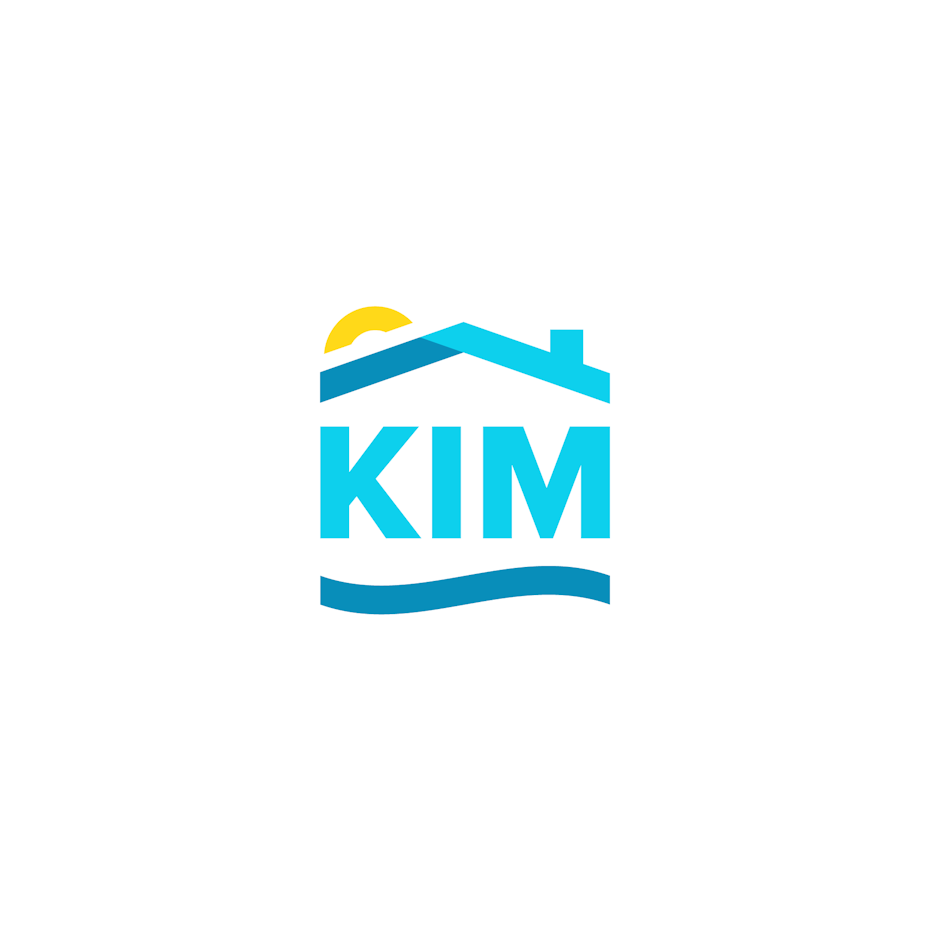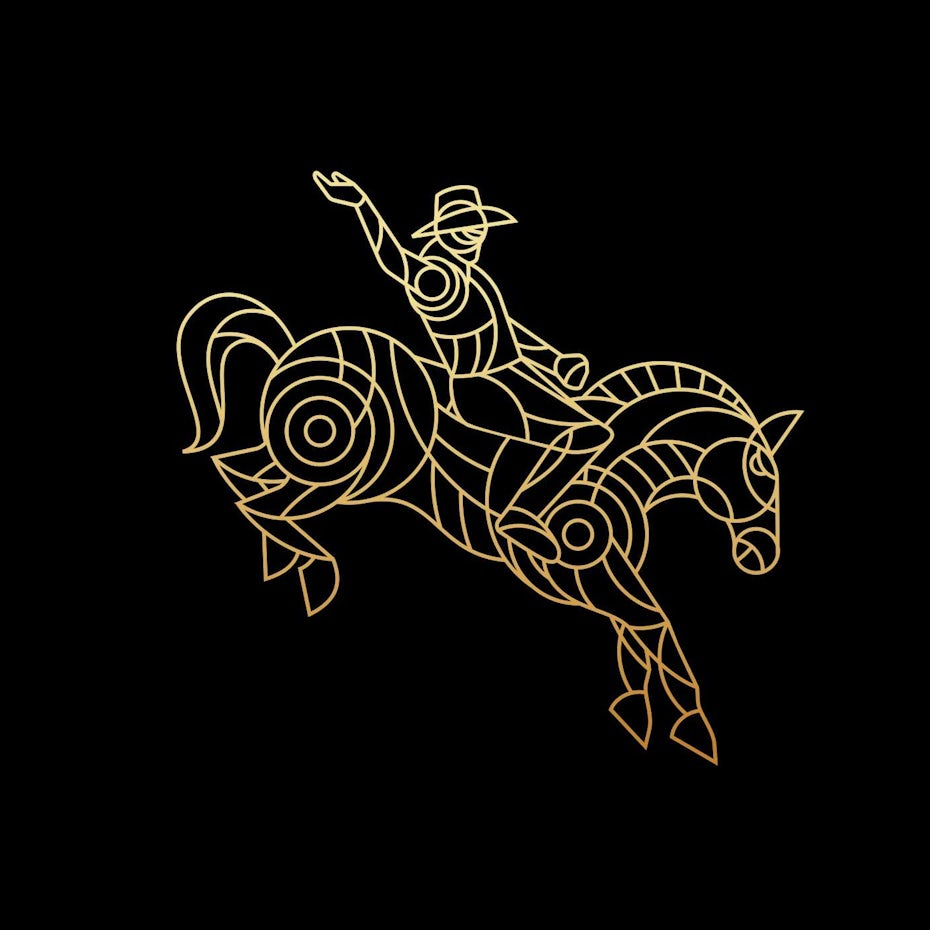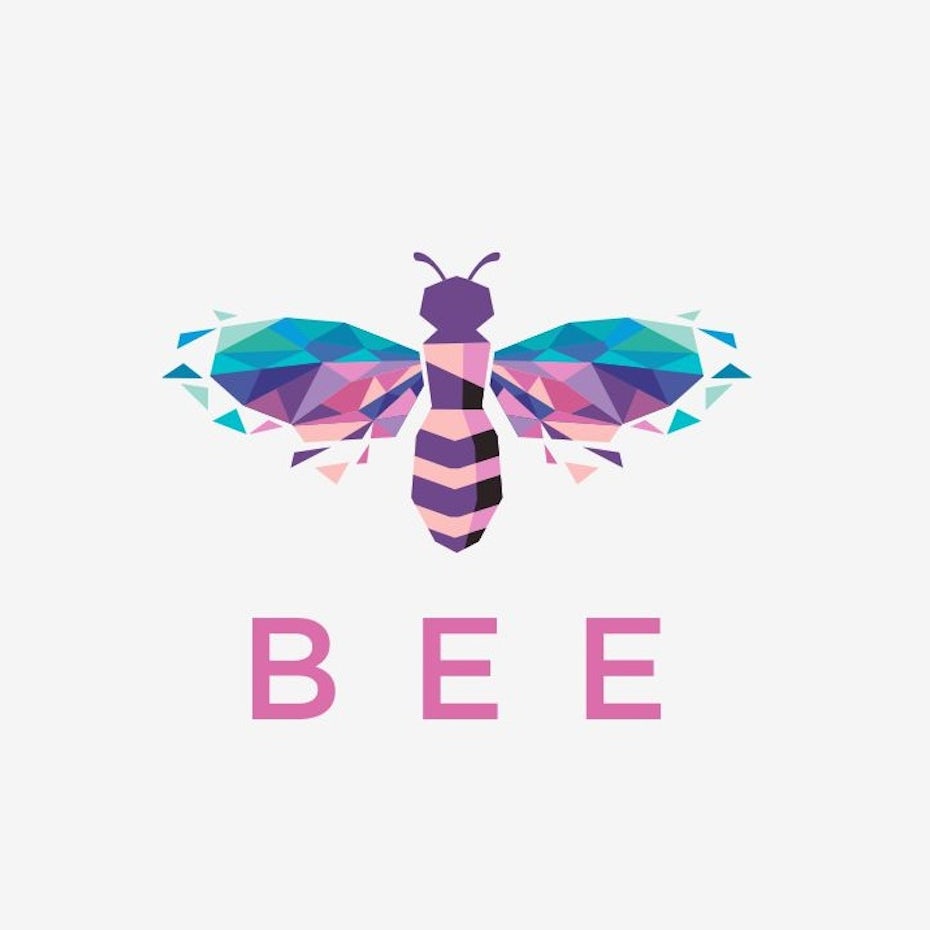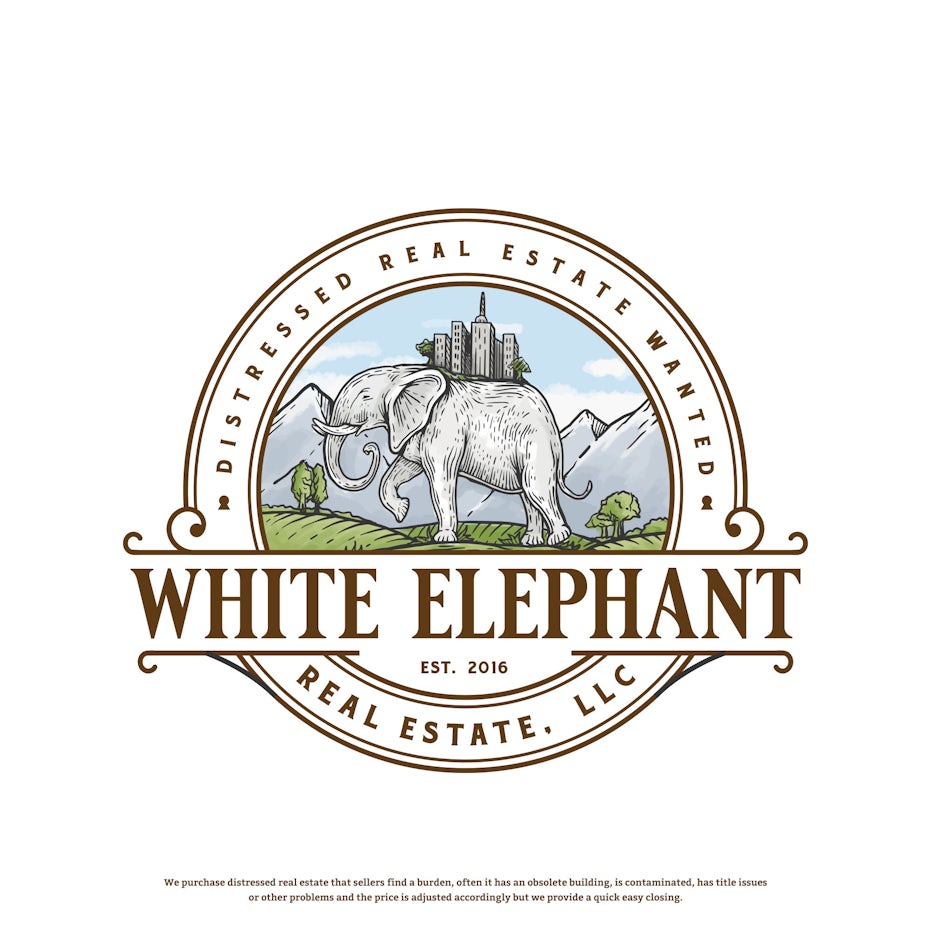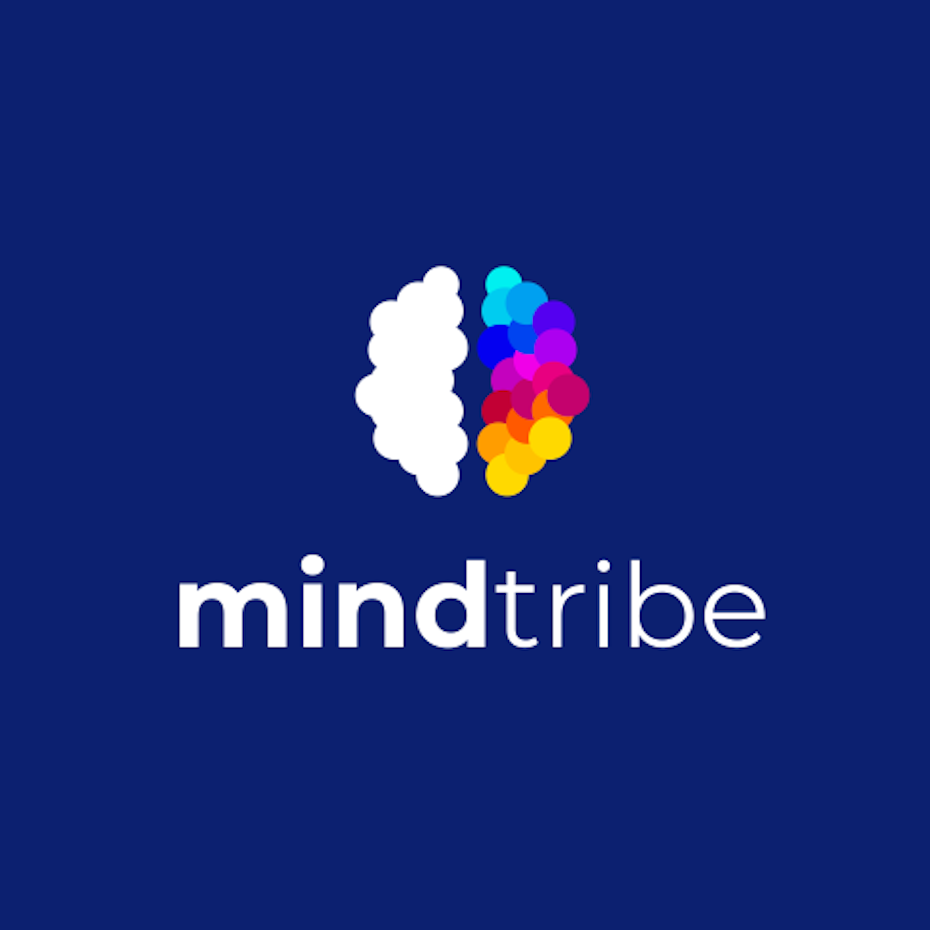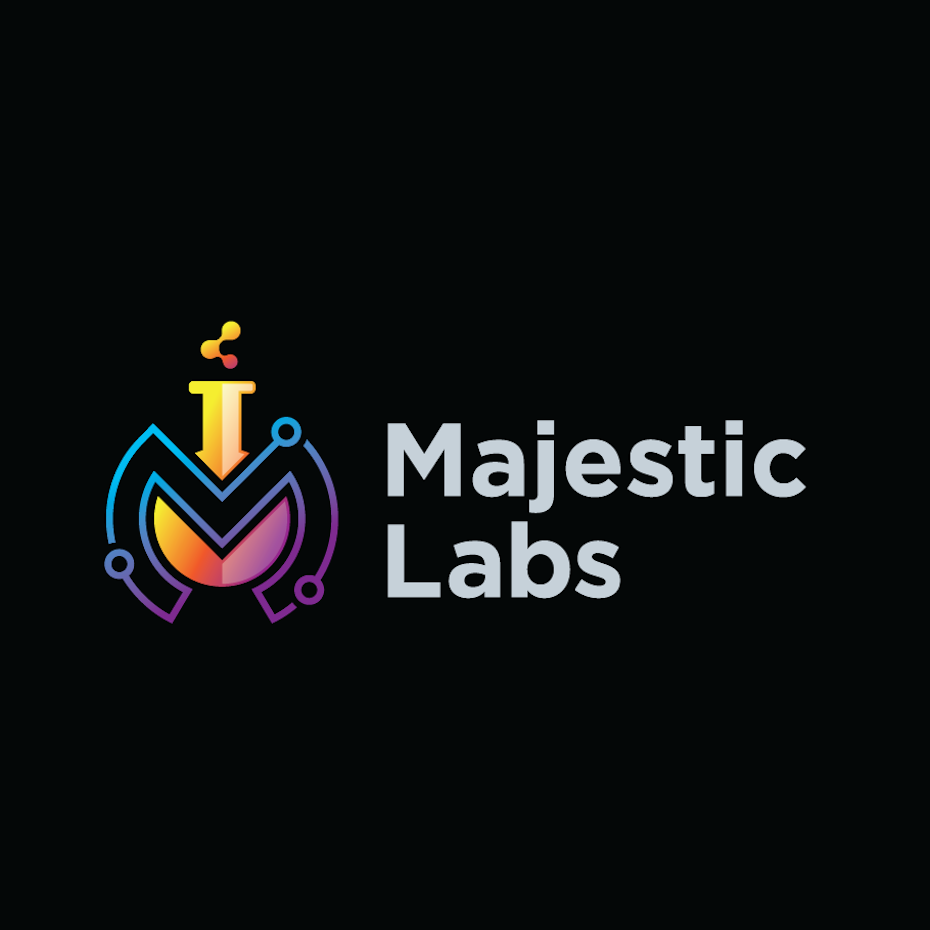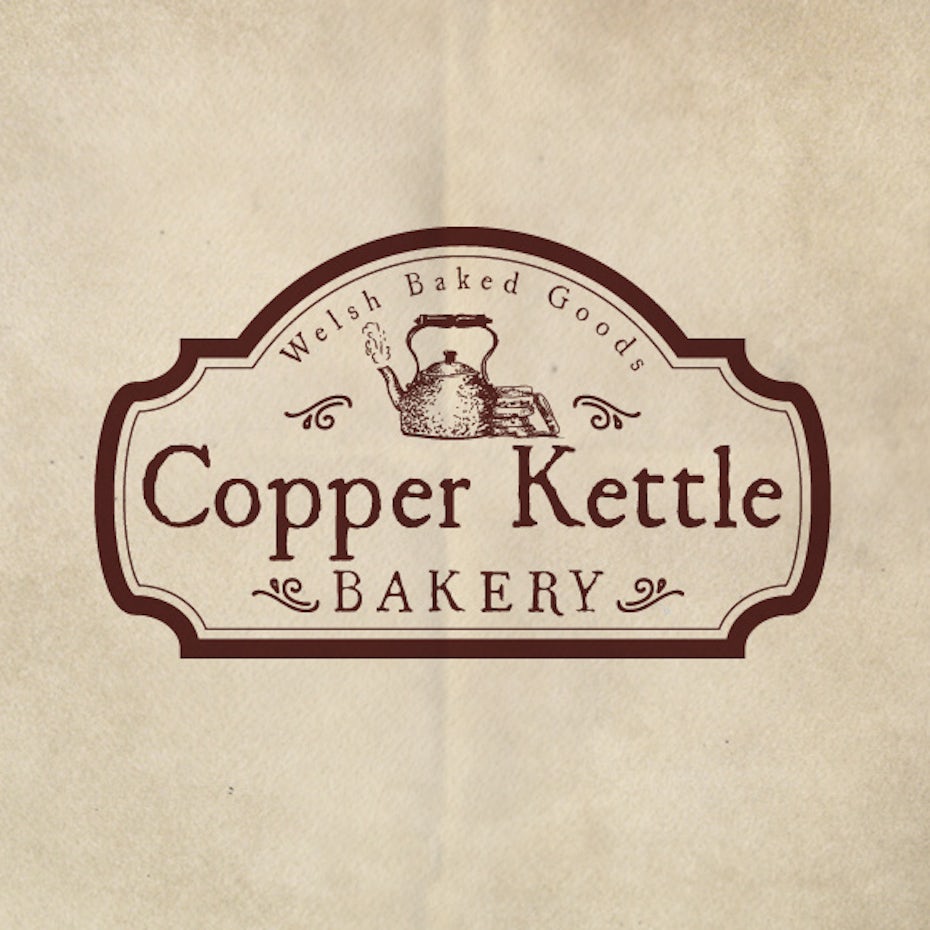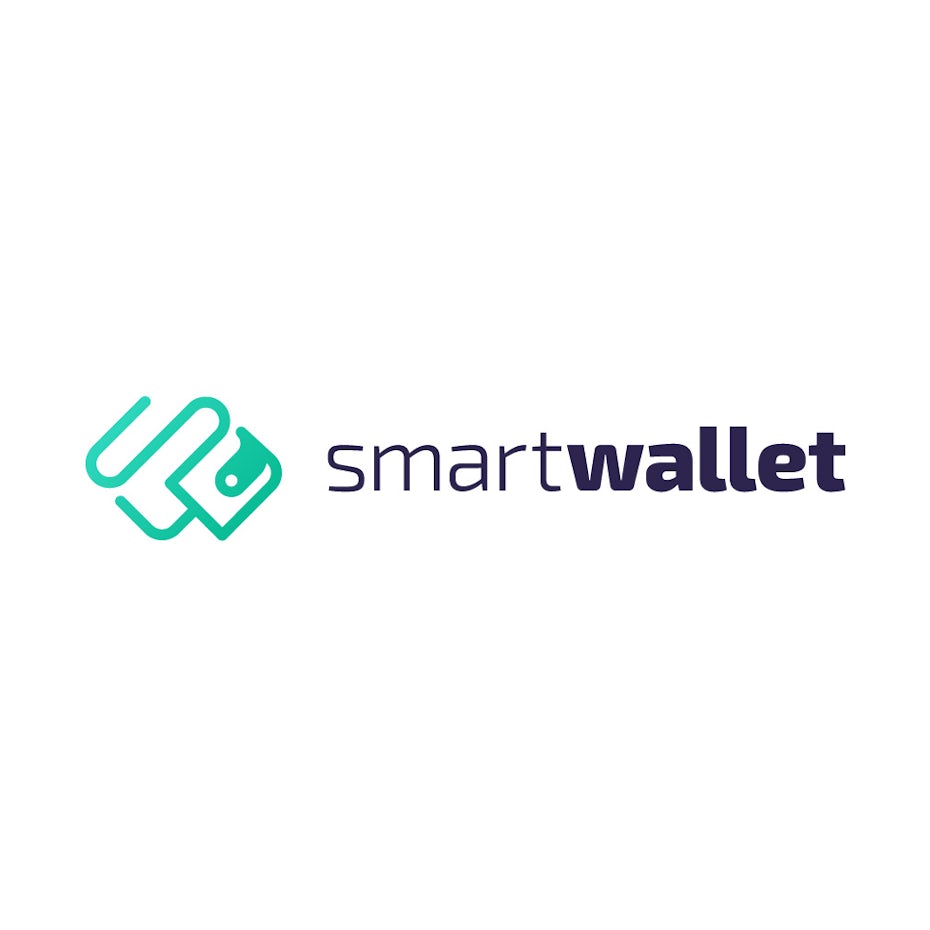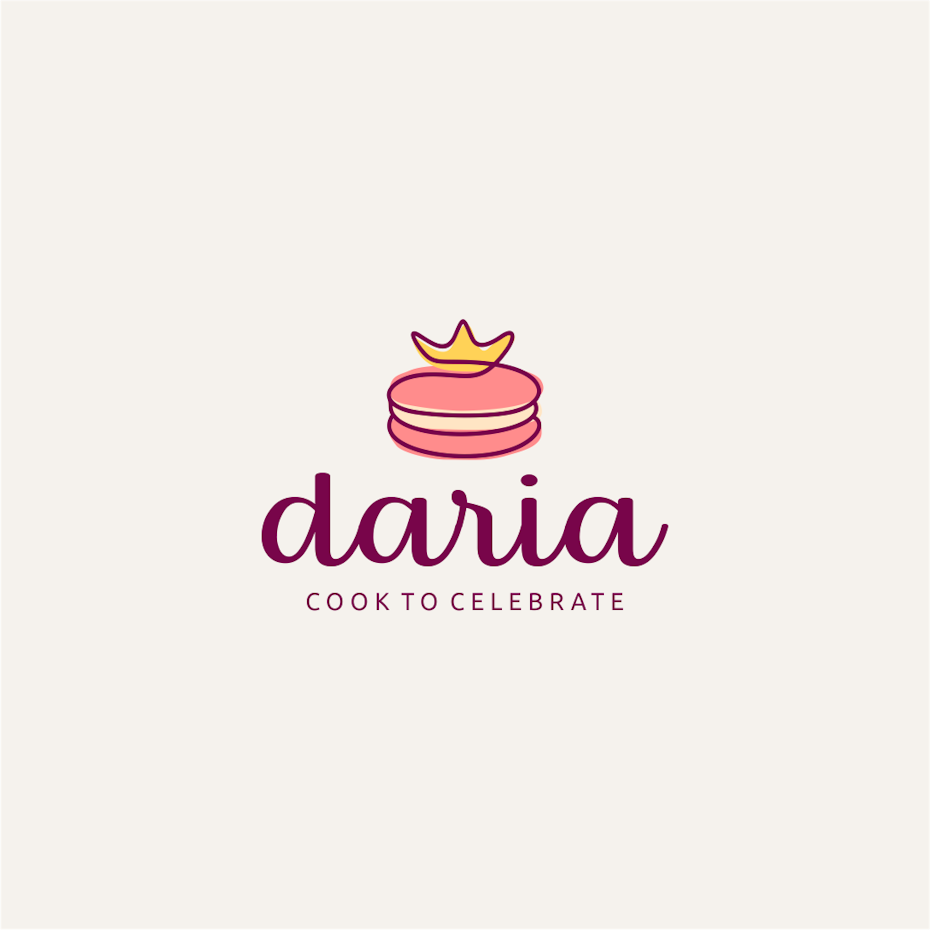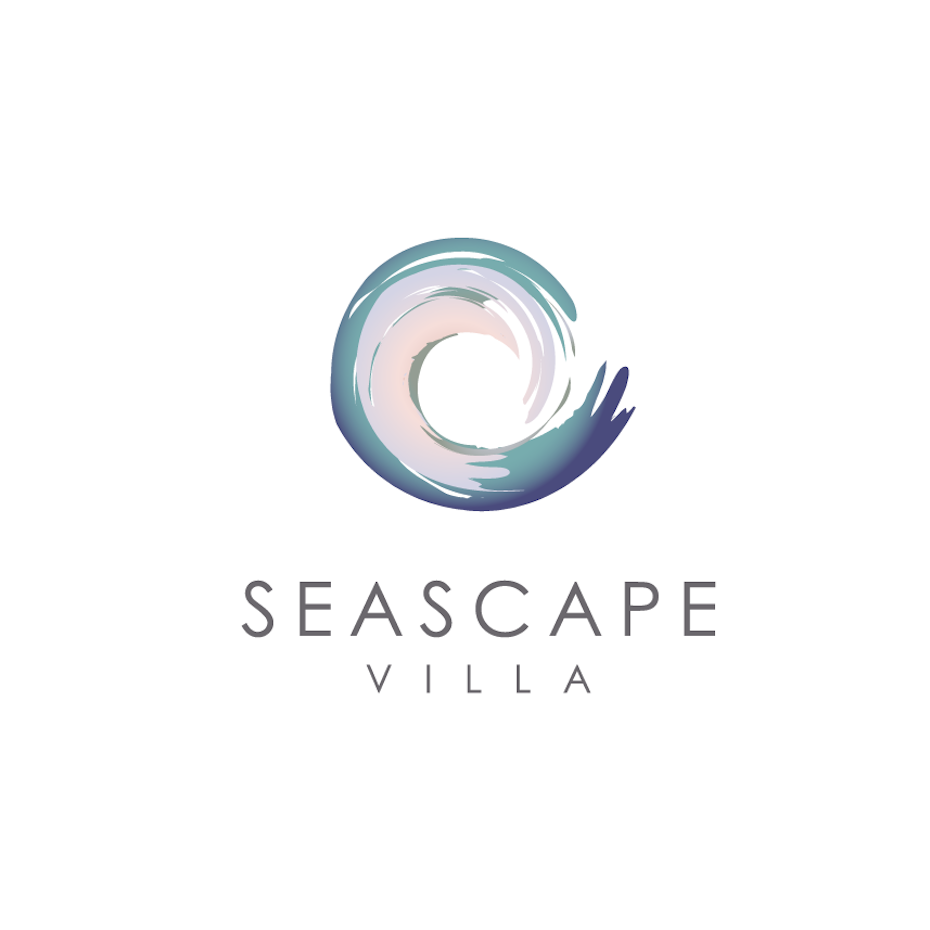
30个永不过时的标志,一些经典的标志设计案例分享
我们生活在一个快速消费和即时满足的世界中,但当涉及到您的公司标志时,标志能够成为“常青树”是我们要走的道路。虽然很容易被设计潮流所左右(每个人都想被视为酷的新生),但选择长寿而不是街头信誉将有助于你创造一个经得起时间考验的永恒设计标志。
复古永恒标志
这些标识提供了颗粒状的纹理,有时甚至是模糊的,它对旧的印刷机增添了情感,怀旧的感觉。复古徽标往往有一个边框,其中包含徽标,有时似乎是手绘的,例如P2。
回到今天,这种风格只可能是单色的,但添加色彩赋予其现代风格,如P3白象房地产标志。
复古永恒的标志适用于传统公司或存在很长时间的公司,如文具品牌或制造皮革制品的公司。复古风格为您的标志带来永恒的感觉,因为它有目的地倾向于过去。传统的复古标志告诉您的客户,您的品牌永远存在,并且永远存在 - 无论何时实际成立。
极简永恒标志
永恒的标志设计不应该过于复杂。向大量受众传达信息的最佳方式是保持简单。线条艺术,几何形状和无衬线字体排版是创造简约,现代和永恒标志的绝佳工具。
极简主义的永恒标识易于理解,并且可以被大众快速识别。这些是永恒标志的一些例子,它们从农业到室内设计,一举通过简单的质量标识来概括业务。
单色永恒标志
首先,单色标识通过避免多种昂贵的彩色墨水在打印时承诺了更好的价值。它们看起来也比花哨的颜色更年轻,明亮,如霓虹色更干净,更经典。
使用单色徽标,您可以在徽标中包含更多细节,因为调色板不显眼,为其他地方提供了更多实验空间。有时很难用复杂的标识来填充,因为它们可能会使观众感到困惑。
这种风格适用于希望保持简单并且同时显得精致的专业服务公司。
彩色永恒标志
如果你要使用颜色,我们建议你坚持使用原色,并尽量减少调色板的使用。你甚至可以在单色的基础上增加一个额外的颜色,或者使用相同颜色的不同色调,比如金氏地产的蓝色色调和伊甸园的绿色标志。
这是一个很好的选择,对于那些经常与某些颜色组有关的行业,如健康和环保品牌的绿色阴影。颜色可以很强,你必须小心不要过火。你可以通过在你的标志中战略性地放置有意义的颜色,以一种永恒的方式整合它。
永恒的印刷标志
构建永恒徽标的绝佳方法是坚持使用经典字体并将其作为徽标的焦点。不要试图通过选择完全无法解读的东西成为特立独行者(即使你认为它看起来很酷)。其中许多例子甚至没有将第一个字母大写,以便在一个统一的层次上保持简洁,而不是整个页面的潦草。
如果选择更自由流畅的风格,请确保单词易于阅读,就像优雅的Polarfuchs示例一样。这些服务适用于那些不想过度复杂化服务的服务型公司,或者需要拉动一些心弦的企业,例如宠物或玩具行业。
如果您的公司围绕一个服务或单词,为什么不在设计永恒的徽标时专注于此?动物就是一个很好的例子:一匹马代表牛仔竞技,一匹吠叫狗为Woof Boost提供狗步行服务,一只蜂鸟用于同名餐厅。将一个主题描绘将为您的企业带来永恒的象征,您可以坚持数十年。
这些徽标使用的图像甚至可以作为剪裁轮廓进行识别。该信息适用于所有语言和字母表,因此这种永恒的标志风格也非常适合国际品牌。
时间永恒
无论您的计划是什么,拥有永恒的标志都是您品牌的坚实基础。通过这些例子作为灵感,您可以创建一个标志,可以摒弃时间,并将继续为后代捐赠。